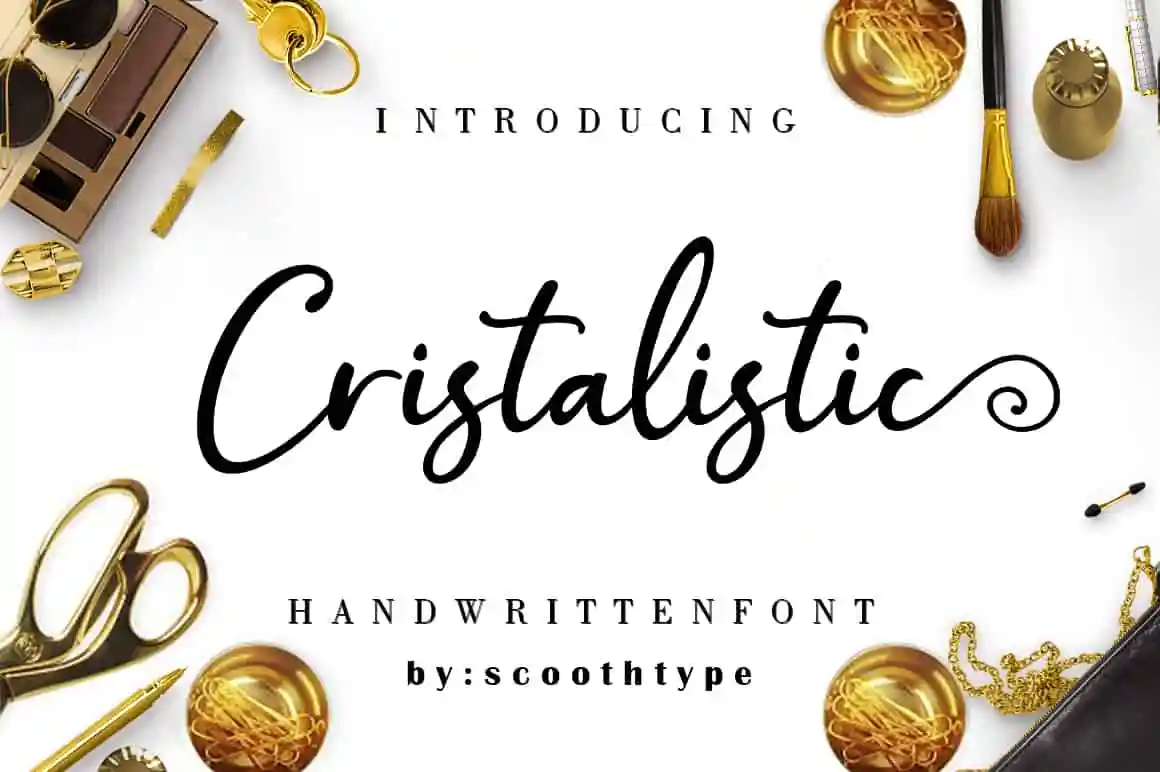
Cristalistic Script Font – Download Grátis
Aqui está uma versão curta e envolvente para a descrição da fonte Cristalistic Script Font na categoria Handwritten Fonts: Descubra Cristalistic Script, uma elegante e suave fonte escrita à mão que vai adicionar um toque de sofisticação ao seu design. Esta fonte foi criada por scoothtype e traz texturas sutis e linhas fluidas, perfeita para criar layouts modernos e atraentes. Confortável para leitura, Cristalistic Script é uma ótima escolha para títulos grandes ou textos mais detalhados. É especialmente adequada para aplicativos de design gráfico, editoriais digitais e criação de logotipos. Esta fonte escrita à mão não apenas tornará seus projetos mais atraentes, mas também adicionará um toque único e pessoal. Se você está procurando por uma fonte que combina elegância com facilidade de uso, Cristalistic Script é definitivamente para você. Descubra agora em nosso site o poder de adicionar um design distintivo ao seu trabalho.
Designer: scoothtype